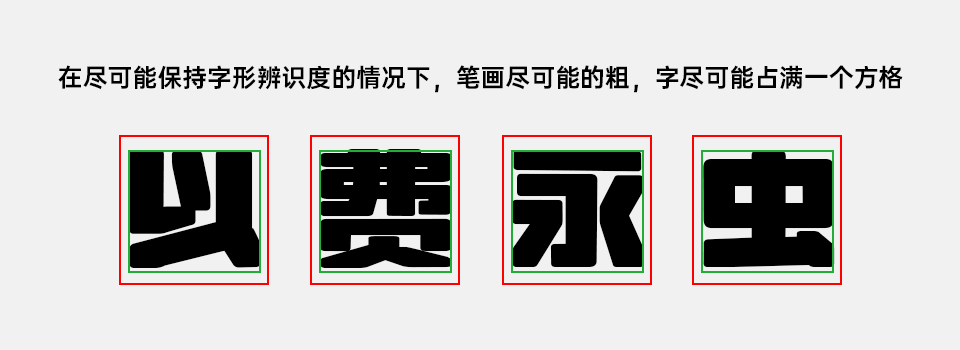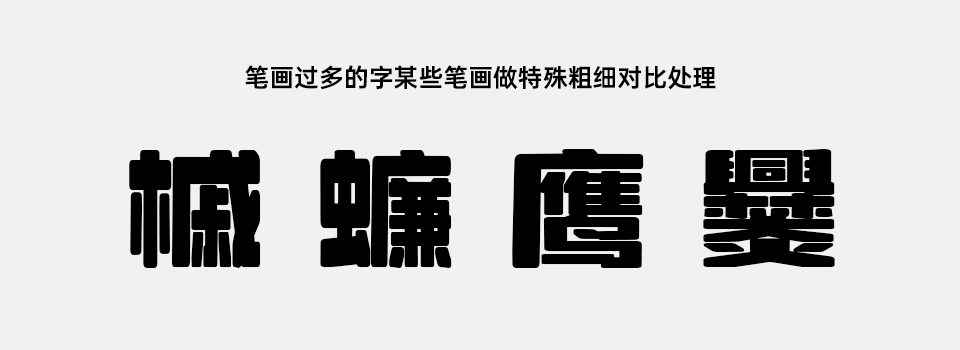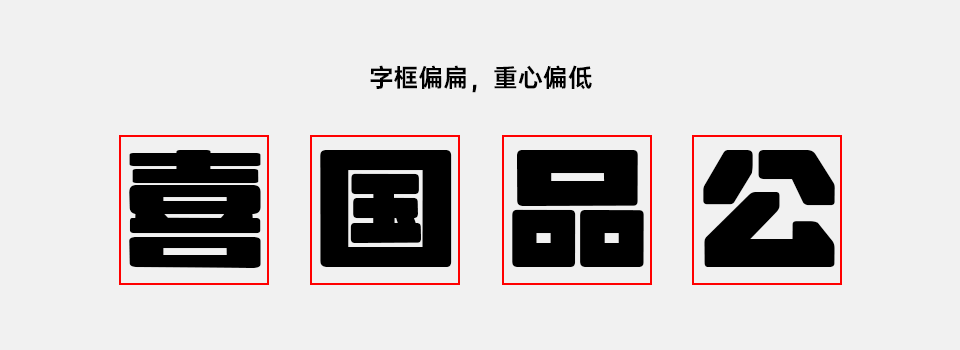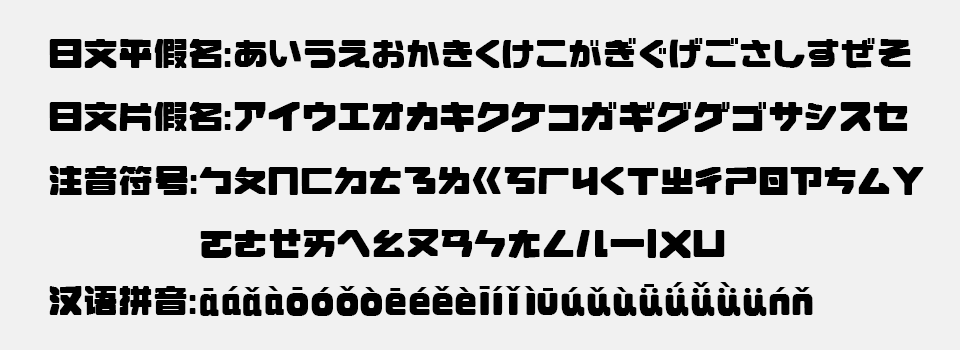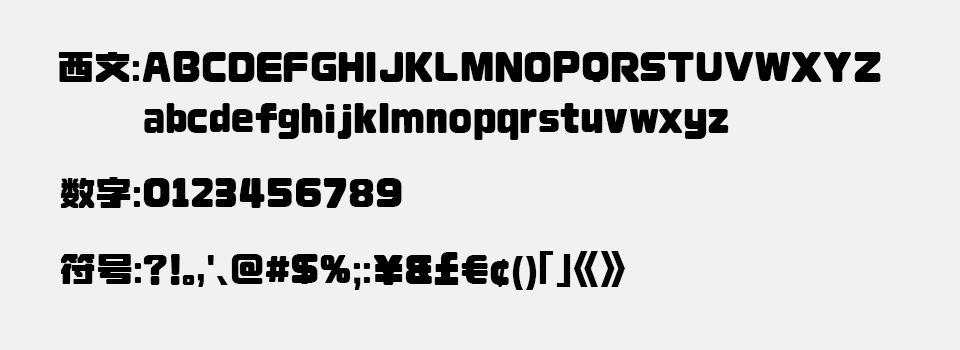
荆南缘默体(Kingnamype Yuanmo SC)是由荆南字坊在 2020 年疫情期间专为标题设计的一款免费可商用美术字体。包含简繁中文、西文、数字、符号、日文假名、注音符号等,近 7000 字。
设计上,作者在保持字形辨识度的前提下,让每个字尽可能的占满一个方格,且笔画也做了加粗处理。而对一些笔画较多的汉字(如 “赢”” 麟 ” 等)则做了特殊粗细对比处理,也确保了其在粗笔画下可以照样保持良好的可读性。笔画末端的圆角处理是后来添加的,让原本充满力量感的黑体也增添了一丝圆体的美术感和趣味性。
也正是因为笔画过粗的原因,所以荆南缘默体并不适合用于正文排版,而是建议使用较大字号(24pt 以上)的应用场景,比如店铺招牌/门头设计,地铁/公交站广告海报、视频封面、VLOG 标题等。